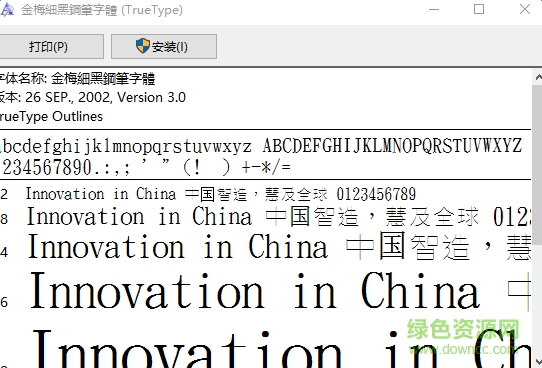
軟件介紹 軟件標簽: 金梅字體 字體 金梅細黑鋼筆字體是金梅字庫中的一款鋼筆字體,寫出來字就和鋼筆寫出來的字一樣好看,也是很實用,用于藝術設計、廣告設計都是很不錯的,歡迎有需要的朋友來綠色資源網(wǎng)下載。金梅細黑鋼筆字體安裝說明第一種1.下載字體并解壓縮;2.開始中打開控制面板;3.在控制面板中打開字體文件夾;4.把下載的字體復制到此文件夾下;5.文字添加完成第二種1.下載字體并解壓縮;2.把文件根目錄下的字體壓縮包解壓縮;3.把文件根目錄下的安裝字體.bat放到含有字體文件的文件夾中,雙擊安裝字體.bat軟件;4.文字添加完成溫馨提示:本站所有字體資源僅供個人學習與參考,如需商業(yè)使用請到相關官網(wǎng)授權 軟件截圖 上一張下一張(1 / 1) 安裝詳細截圖 猜你喜歡 鋼筆字體 金梅字體 鋼筆字體 鋼筆字體是設計領域經(jīng)常用到的字體,鋼筆字體具有鮮明的個人特征,風格多樣,深受廣告設計、平面設計師的喜愛,除了一些手寫鋼筆字體,還有正楷、行書類的鋼筆字字體,為設計師們提供了豐富的字體形式,綠色資源網(wǎng)也有很多鋼筆字體下載和鋼筆字體包,需要的可以看一看 查看更多>> 鋼筆書法軟件手機版 103.96MB/中文/10.0/v2.2.0 安卓版下載 鋼筆之家 4.83M/中文/10.0/v1.0.2 安卓版下載 鋼筆手寫字體免費 11.71M/中文/1.2/下載 鋼筆書法入門基知識 31.79M/中文/5.0/v6.3.1 安卓版下載 浮生體 1.92M/中文/5.0/下載 伯樂鋼筆行書字體 3.53M/中文/6.6/下載 金梅字體 金梅字體是以繁體字形為主,多數(shù)的金梅字體都是繁體。金梅字體給人的感覺比較多樣,有的比較圓潤,有的比較可愛,還有破裂的字體,于楷體形成了鮮明的對比,沒有固定的樣式。金梅字體多用于廣告制作、海報制作、封面制作等。 查看更多>> winman tun10011字體 17.57M/中文/6.6/下載 金梅浪漫原體國際碼 1.91M/中文/6.6/下載 金梅粗明原體國際碼 1.41M/中文/5.0/下載 金梅流行書 2.78M/中文/10.0/下載 金梅綜藝菱心 4.19M/中文/10.0/下載 金梅浪漫小胖 3.44M/中文/10.0/下載 其他版本下載 標題 大小 更新日期 下載 下載地址 電腦版 金梅細黑鋼筆 點擊報錯 軟件無法下載或下載后無法使用,請點擊報錯,謝謝! 關閉報錯反饋 請描述您所遇到的錯誤,我們將盡快予以修正,謝謝! *必填項,請輸入內容 本類最新 金梅海報美工體 金梅新箭頭字范例字體 免費版 金梅特黑水花字形字體 免費版 金梅粗尖頭字范例繁體字體 免費版 金梅淡古字ttf 免費版 金梅浪漫鏡射體 相關文章 Photoshop字體安裝使用方法和技巧 如何解決“無法新增字體”問題 Win 7系統(tǒng)安裝字體方法 網(wǎng)頁字體大小設置方法 怎么改網(wǎng)頁字體大小 在Linux系統(tǒng)中安裝字體的幾種方法 windows7字體顯示問題:打開某些程序的時候顯示的是亂碼 用戶評論 熱門評論 最新評論 發(fā)表評論 查看所有評論(0) 昵稱: 請不要評論無意義或臟話,我們所有評論會有人工審核. 字數(shù): 0/500 (您的評論需要經(jīng)過審核才能顯示)